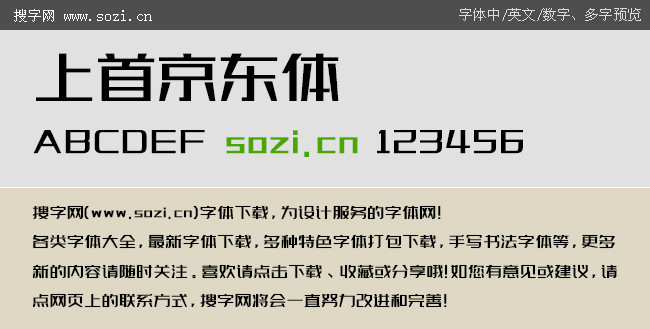
上首京東體
搜字網(wǎng)給大家提供一款上首京東體中文字體下載,上首京東體方中帶圓,上細(xì)下粗,轉(zhuǎn)折圓滑,是此套字庫(kù)的亮點(diǎn)。字庫(kù)整體特征圓柔、輕巧,時(shí)尚,適用于搭配標(biāo)志、廣告標(biāo)語(yǔ)、商業(yè)廣告等高端屬性。